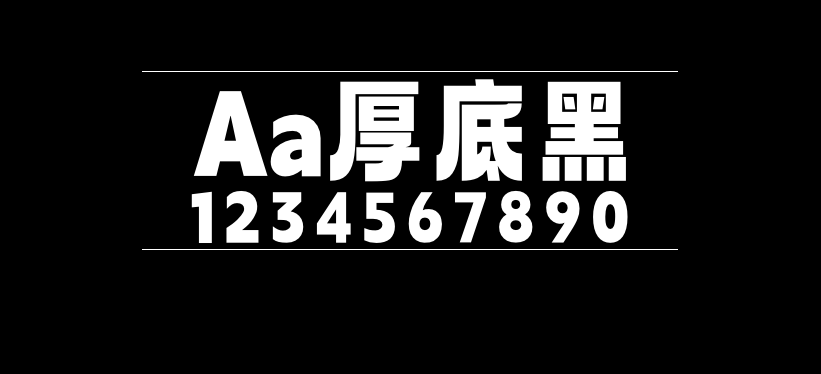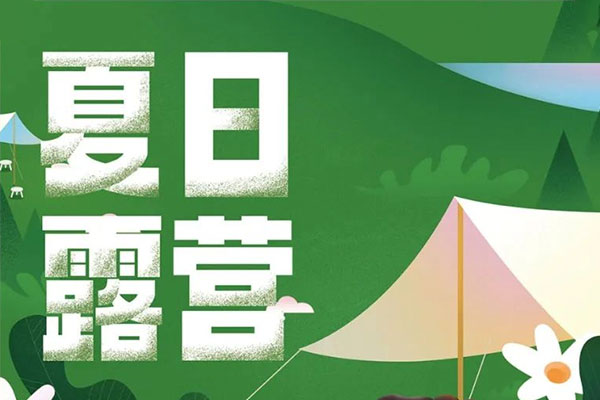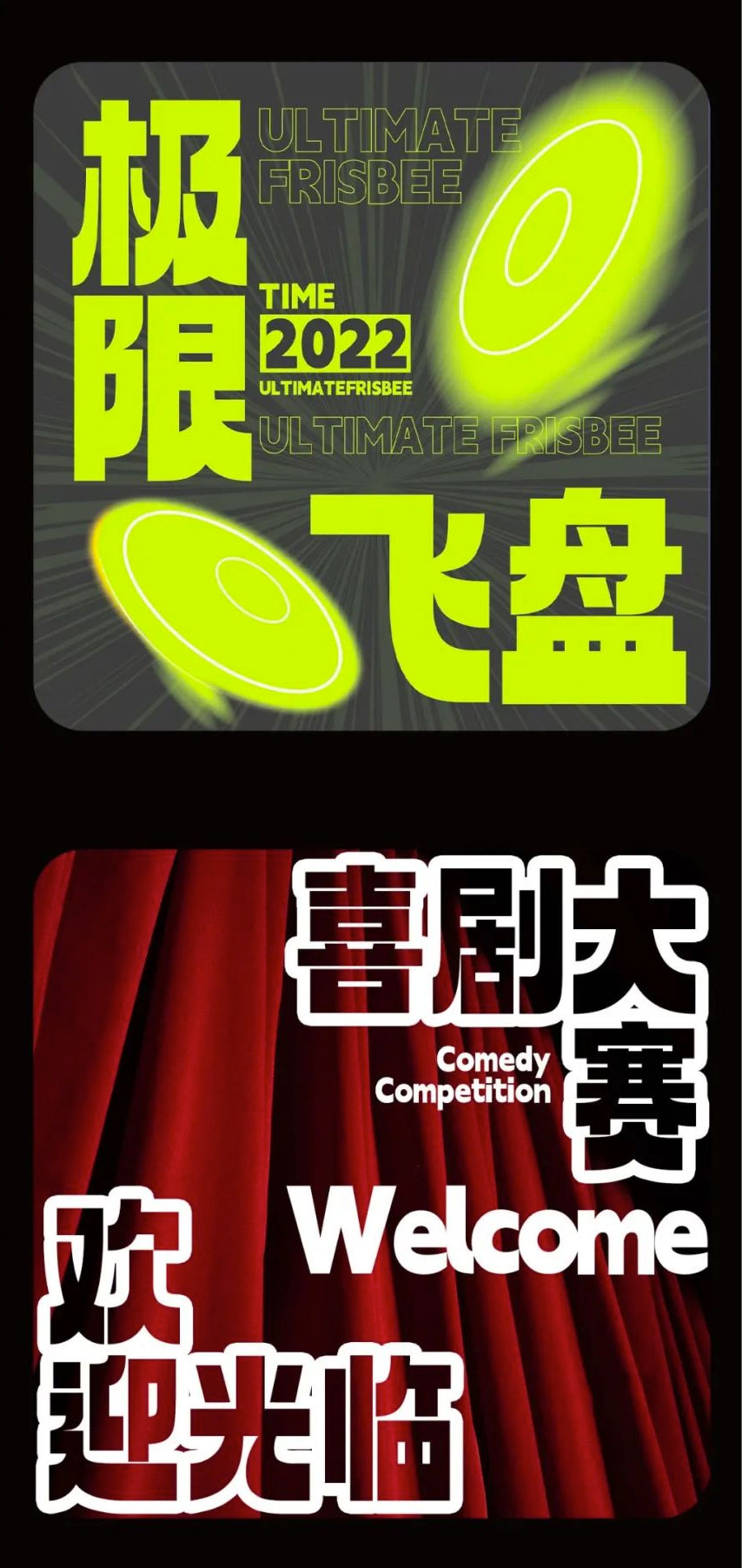
Aa厚底黑
Aa厚底黑字体是Aa字库推出的第二套现代活泼的免费商用美术字体,主创设计师是王梦琪。早在今年4月的时候,Aa字库就跟自由字体透露过将会推出另一款免费字体,今天这款Aa厚底黑终于跟大家见面了。
Aa厚底黑笔画横粗竖细,与传统的字体有较大不同,有点偏酸性字体设计风格。在字型上,用了弧度比较大的曲线让字体更活泼一些。